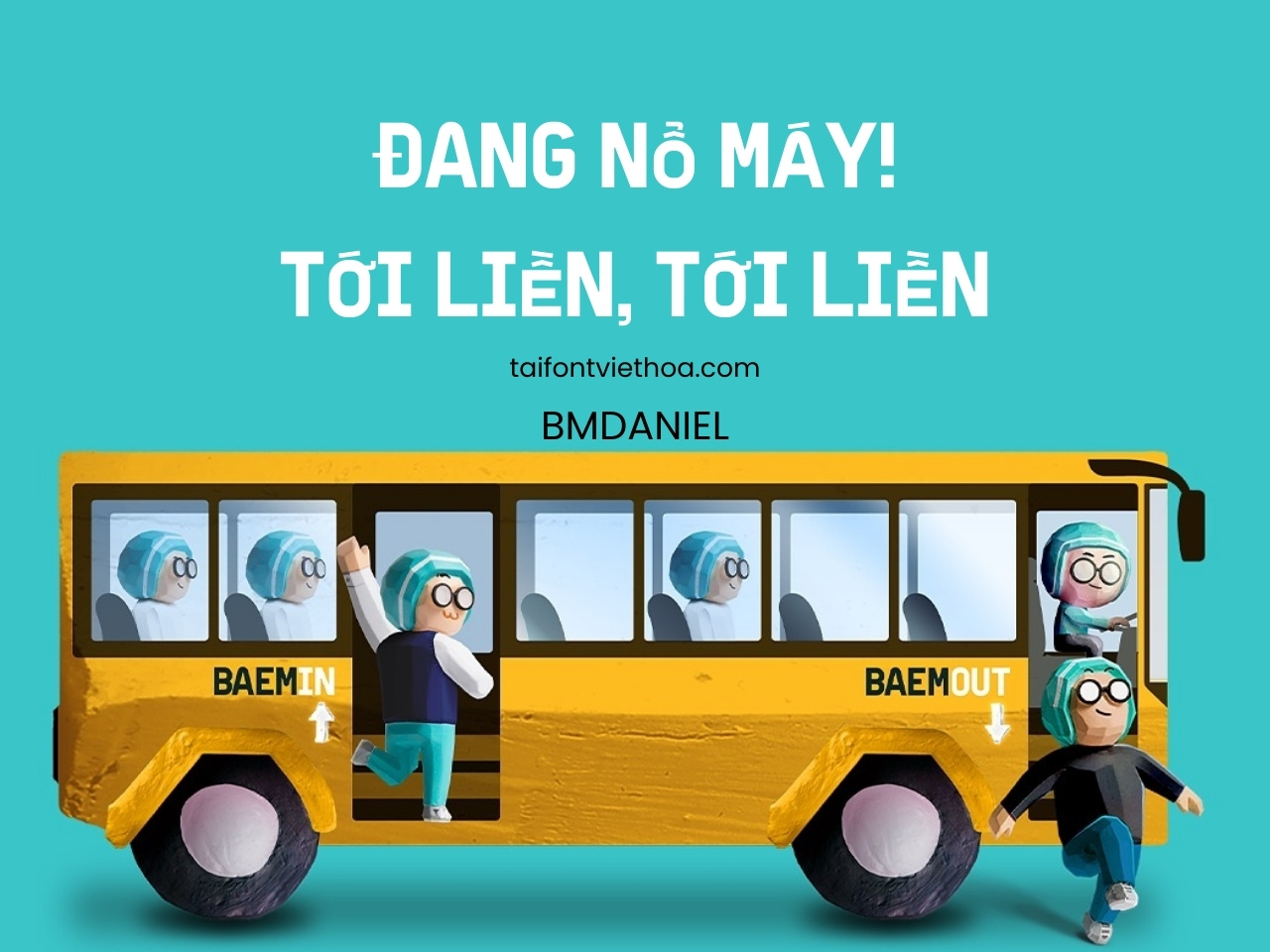
Font việt hóa Baemin Giao Đồ Ăn
Font việt hóa Baemin Giao Đồ Ăn font ẩm thực
Tác giả Font: Rice And Kia Tasbihgou
Giới thiệu font Baemin Giao Đồ Ăn – Font sans-serif thương hiệu từ Rice Creative
Font Baemin Giao Đồ Ăn là kiểu chữ sans-serif được thiết kế độc quyền cho ứng dụng giao đồ ăn Baemin tại Việt Nam. Bộ font này là kết quả hợp tác giữa studio thiết kế danh tiếng Rice Creative và nhà thiết kế Kia Tasbihgou, với mục tiêu tạo nên một kiểu chữ mang đậm cá tính thương hiệu: trẻ trung, dễ thương, hiện đại và đậm chất bản địa. Font không chỉ hỗ trợ đầy đủ tiếng Việt mà còn tương thích với hơn 80 ngôn ngữ khác, được công bố chính thức bởi Rice-Creative.com như một phần trong hệ thống nhận diện thương hiệu toàn diện. Font này đã được taifontviethoa.com sưu tầm và chia sẻ rộng rãi đến cộng đồng thiết kế, nhằm phục vụ các dự án sáng tạo cần truyền tải tinh thần năng động và sự gần gũi với người dùng trẻ.
Thiết kế tròn trịa, vui nhộn và ứng dụng đa dạng của font Baemin
Font Baemin sở hữu cấu trúc sans-serif rõ ràng, mạnh mẽ nhưng được xử lý hình học tròn trịa, các chữ cái có tỷ lệ lớn, tạo cảm giác vui vẻ, hài hước và dễ đọc trên cả giao diện số lẫn in ấn. Điểm nổi bật của font là sự đồng nhất hình khối, cách xử lý khoảng cách chữ thân thiện và khả năng hiển thị tốt trên nền tảng kỹ thuật số. Font được sử dụng hiệu quả trong logo thương hiệu, tiêu đề, giao diện ứng dụng, banner quảng cáo, thiết kế menu, bao bì sản phẩm ẩm thực, và đặc biệt lý tưởng với các ngành như công nghệ giao hàng, ẩm thực, thương mại điện tử, giáo dục trẻ em, truyền thông xã hội và thiết kế UX/UI. Font Baemin không chỉ là một kiểu chữ mà còn là một phần không thể thiếu trong nhận diện thương hiệu sáng tạo tại Việt Nam.